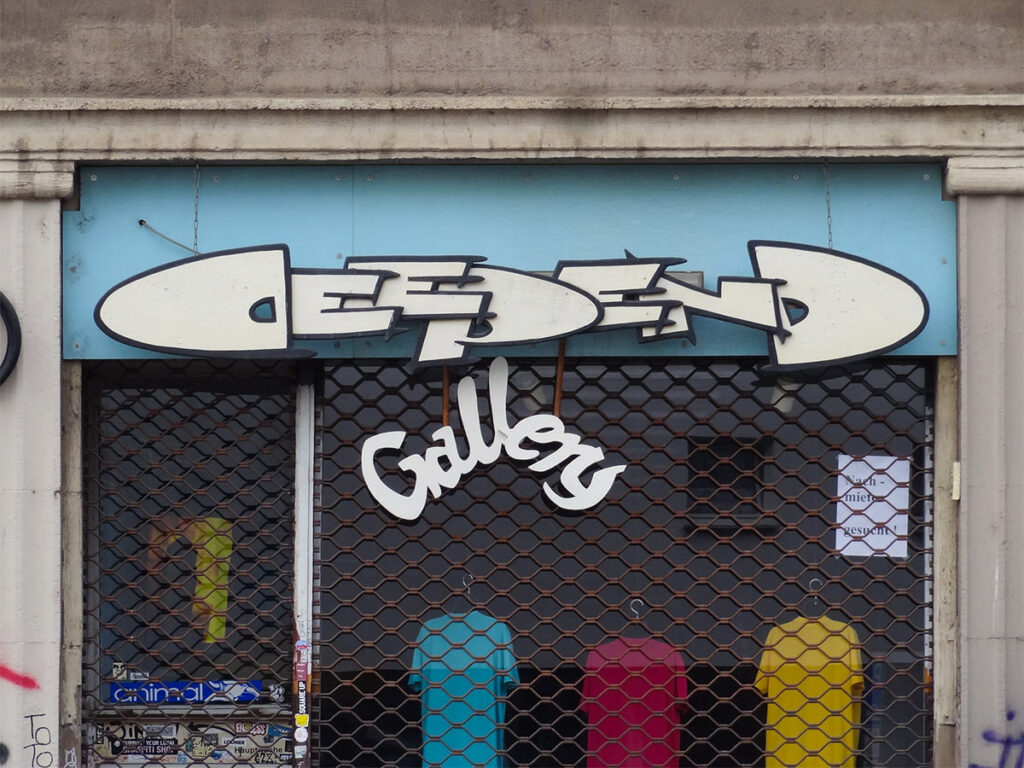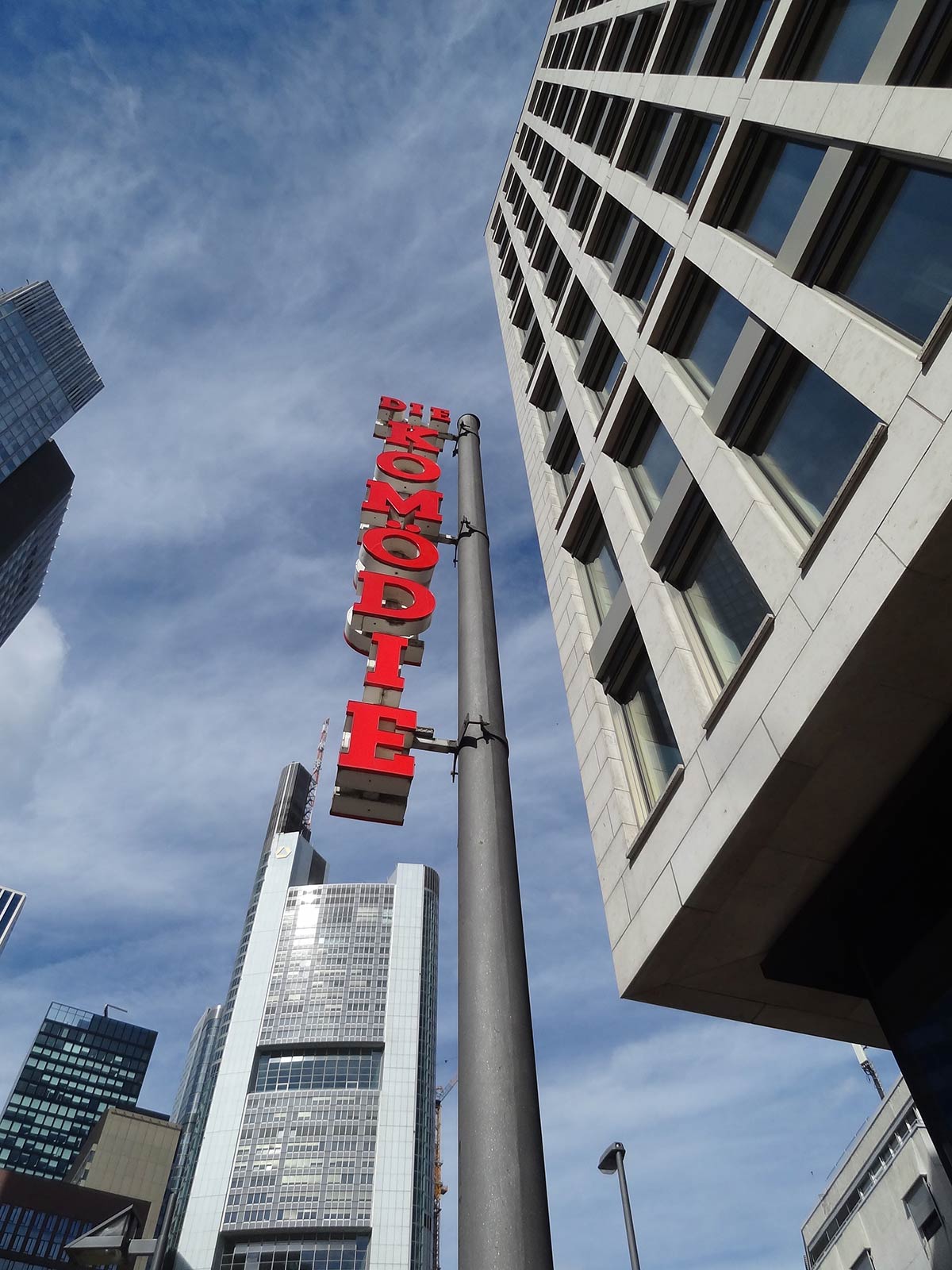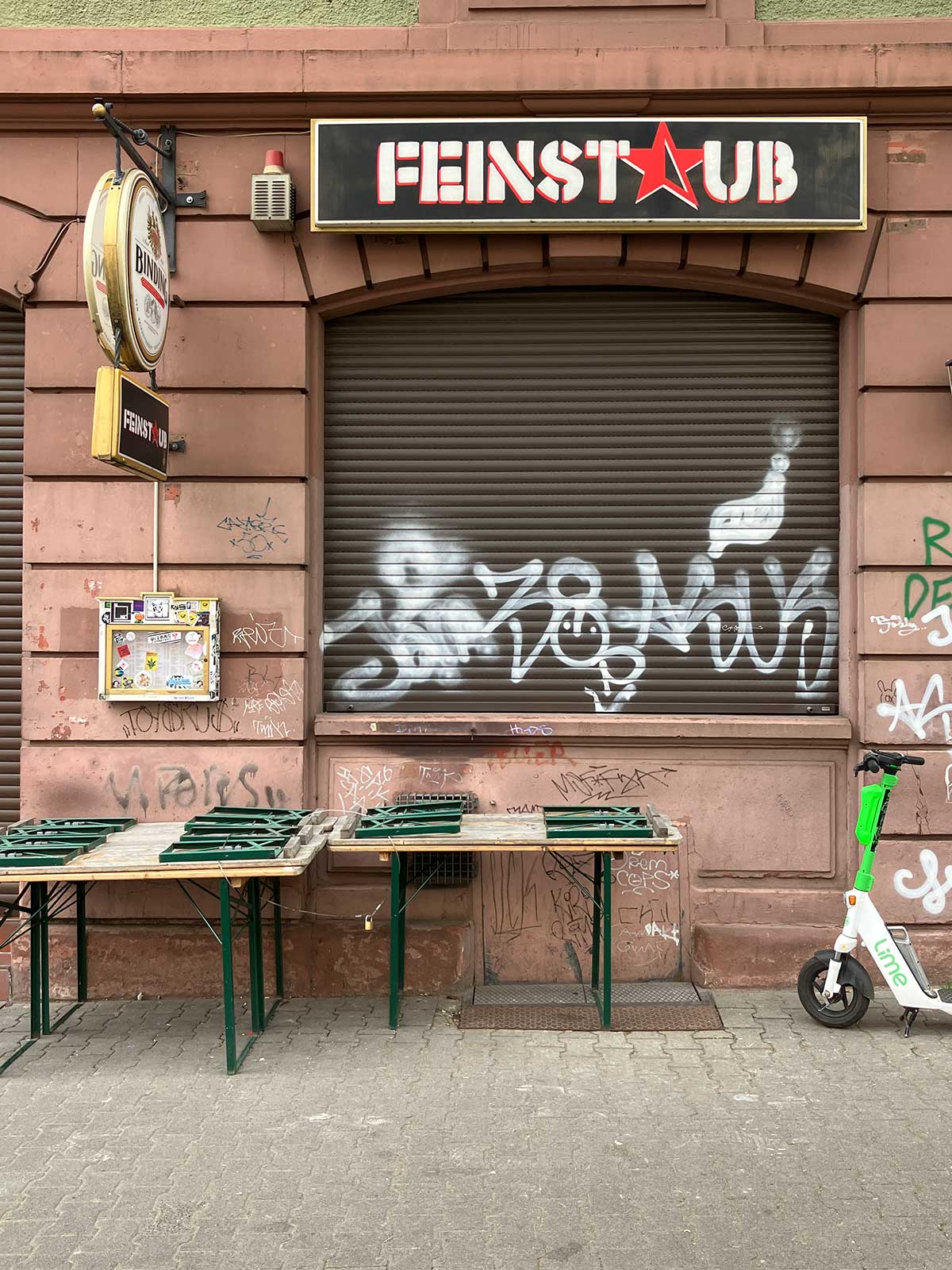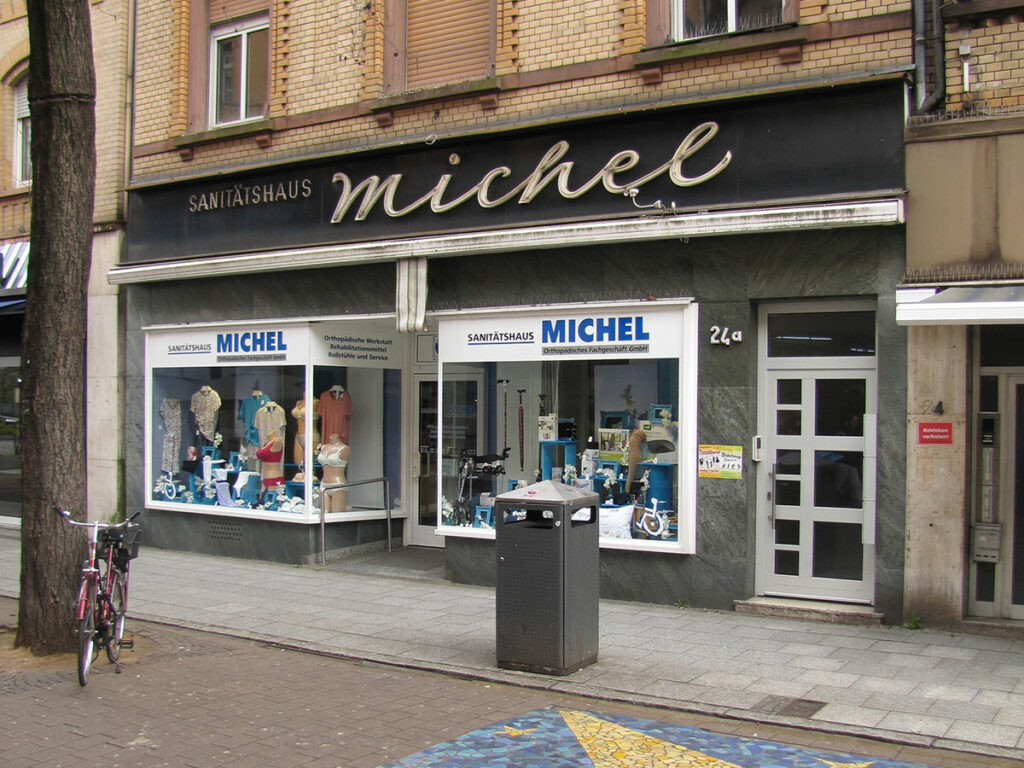
Von der Dippemess bis zur Goethestraße, dem Bahnhofsviertel bis nach Höchst und gebrochenen Schriften bis hin zu Schreibschriften mit kunstvoll geschwungenen Leuchtstoffröhren – Die mittlerweile zwölfte Ausgabe der Reihe Typografie in Frankfurt präsentiert eine vielfältige Auswahl an Gestaltungsbeispielen aus dem öffentlichen Raum Frankfurts.
Typografie in Frankfurt (12)